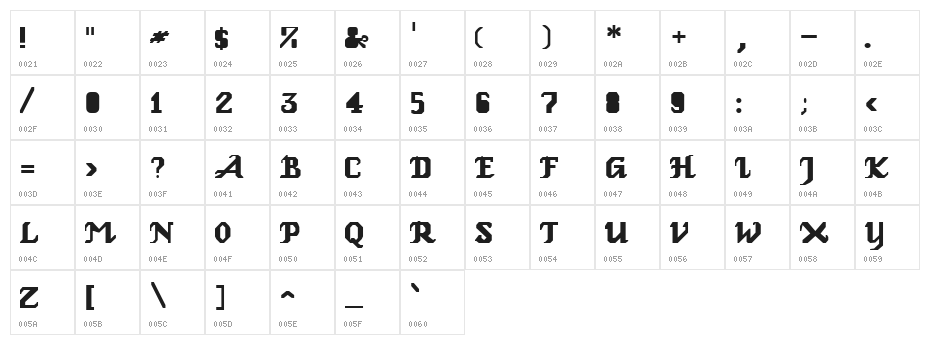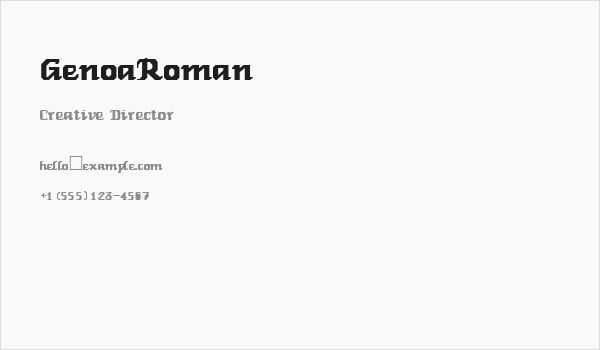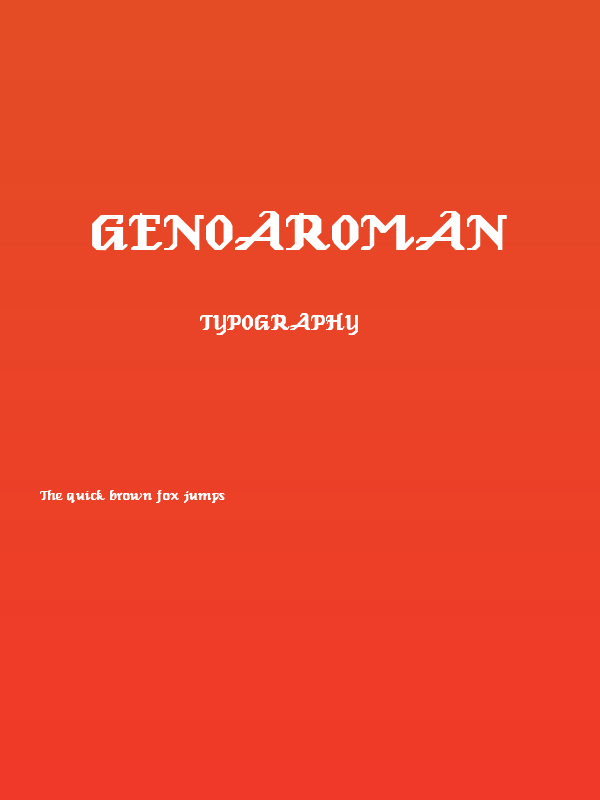
GenoaRoman Font
| Progetti proposti | Ideal for historical-themed designs, book covers, posters, and branding that requires a classic and bold aesthetic. |